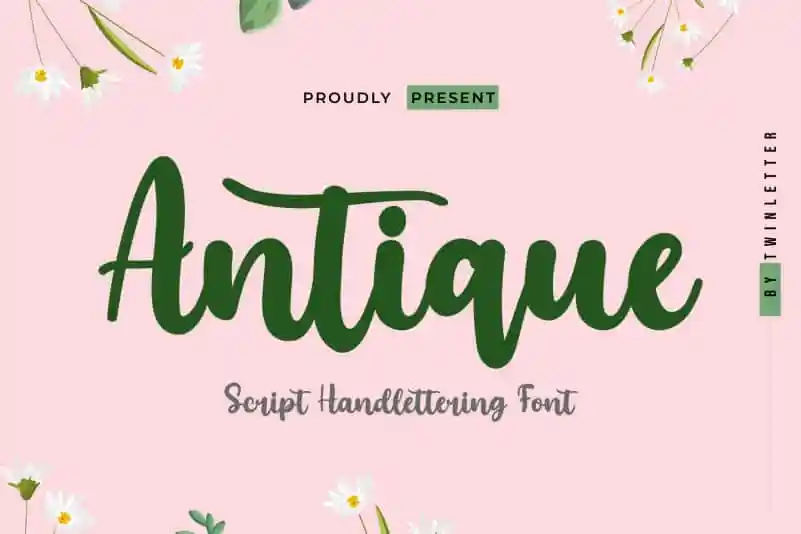
Antique Script Font – Download Grátis
Antique Script Font é uma fonte de estilo brush que transmite um toque suave e elegante ao mesmo tempo. Desenvolvida pelo designer twinletter, esta fonte de escrita humana possui um charme romanesco e alegre, mas sem perder sua beleza natural. Ideal para gráficos pessoais, como cartões de aniversário ou mensagens dedicadas, ou até mesmo em elementos artísticos no design editorial. Com uma textura única que remete à escrita manual antiga e agradável, Antique Script Font é um recurso visual divertido e estiloso para qualquer projeto gráfico. Engane-se, esta não é apenas uma fonte de texto, mas um elemento de design único capaz de dar vida ao seu projeto com estilo antiquado.